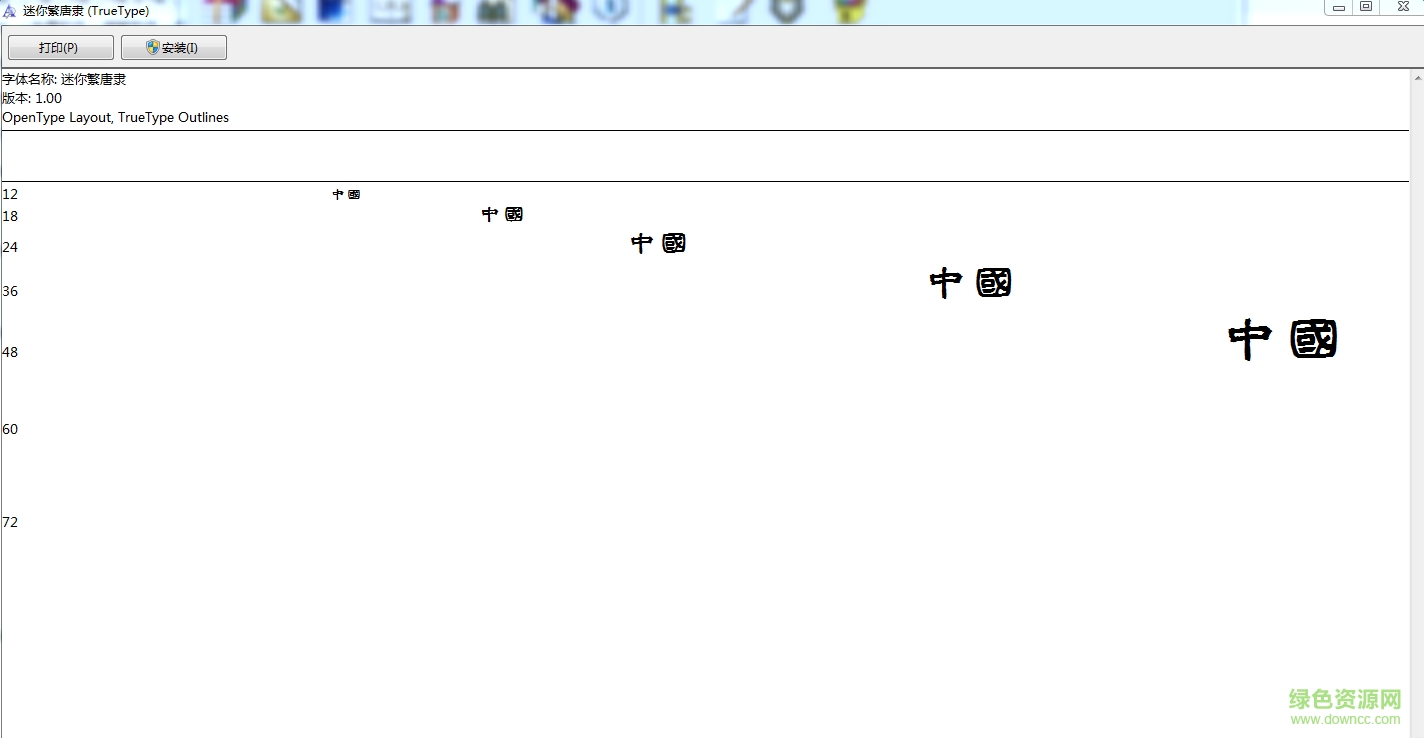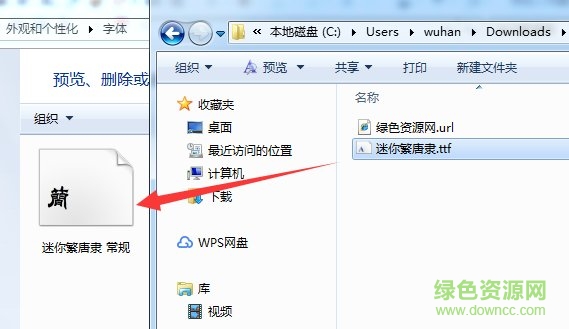
迷你繁唐隸字體使用范圍非常廣泛,這款字體支持簡體繁文輸入,字體輸出的文字效果很不錯。是繁體字體中很美觀的一個資源!能夠在windows和mac系統(tǒng)上安裝使用。
迷你繁唐隸是一款唐朝時期繁體字體,字體效果比較繁瑣,繁體字給人非常古老的感覺,深受廣大書法家的喜愛。喜歡繁體字的朋友可以下載使用看看效果如何。